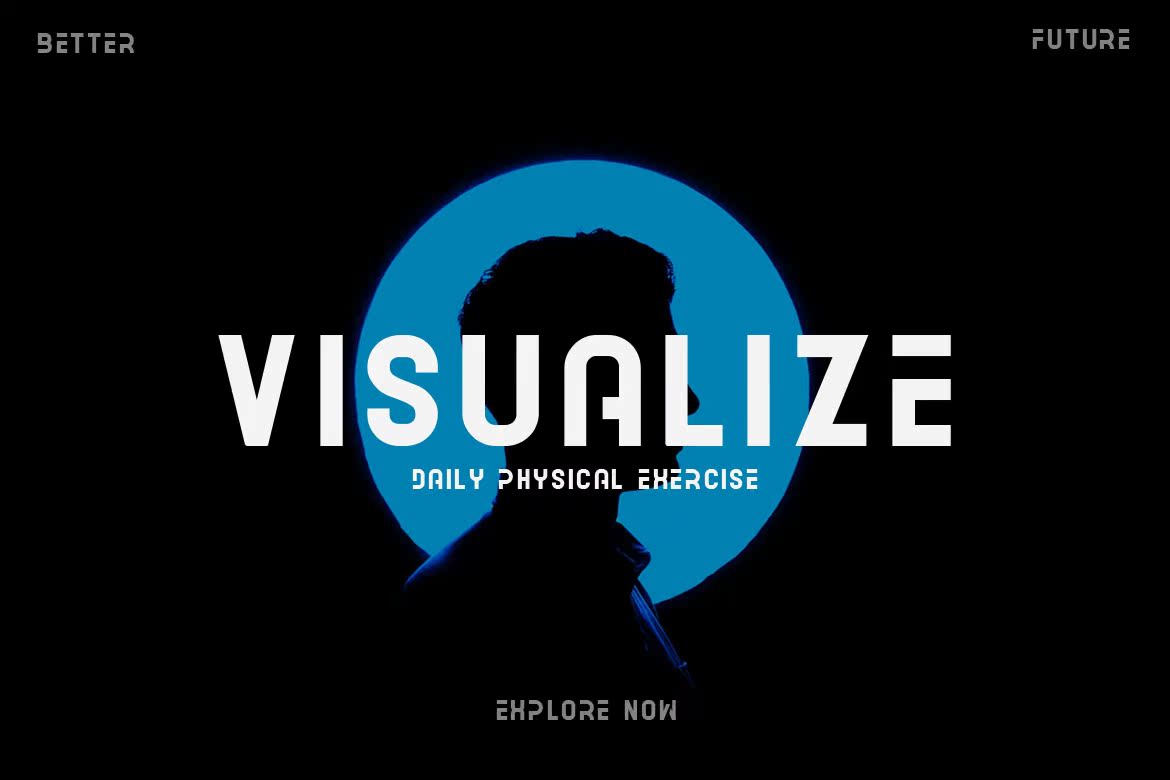
AcetoneisafuturisticFontfordesignofminimalisticLogo和Rebrand。可用于创建文字标记、标题、封面、标语和内部主题的内容。FullVersionDownload此处:AcetoneisafuturisticFontfordesignofminimalisticLogo和Rebrand。可用于创建文字标记、标题、封面、标语和内部主题的内容。FullVersionDownload此处: